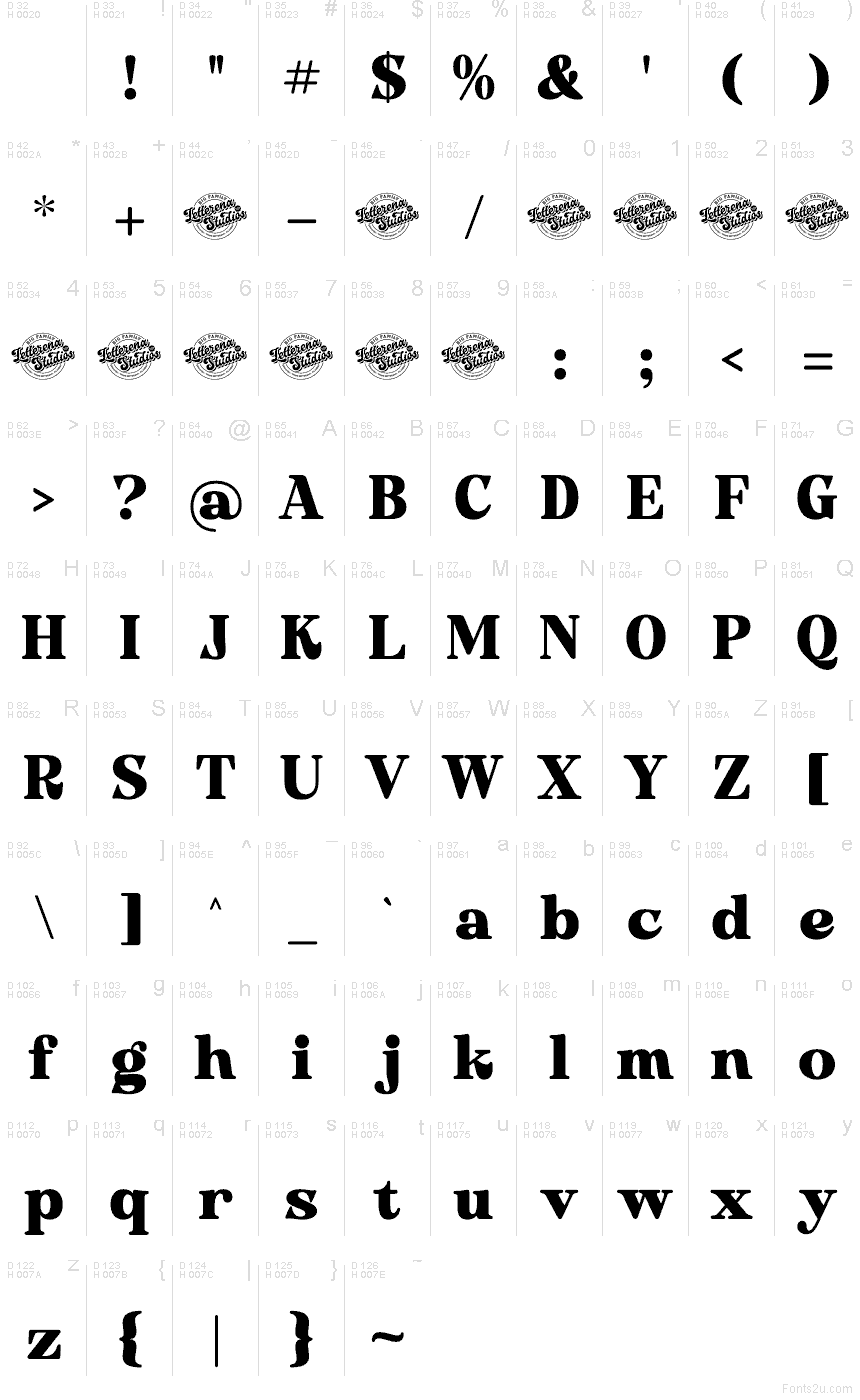
Begsta Pearl DEMO VERSION
Begsta Pearl aus dem Hause Letterena Studios ist eine kostenlose Retro-Serifenschrift mit dem unbeschwerten Lebensgefühl der 1970er Jahre. Die Buchstaben wirken üppig und fast ein wenig fließend, mit schweren Rundungen, engen Verbindungen und tropfenartigen Details, die der Schrift einen verspielten, plakativen Rhythmus verleihen – weit weg von formellem Buchsatz.
Sie eignet sich hervorragend für Branding-Projekte, Café-Speisekarten, Albumcover, Verpackungsdesigns und Magazin-Titel, bei denen eine sanfte Vintage-Note gefragt ist. Als kostenlose Schriftart glänzt sie besonders bei kurzen Überschriften, Titelkarten und logoartigen Schriftzügen, da die abgerundeten, vollen Formen selbst kurzen Wortfolgen eine entspannte, unverkennbar nostalgische Ausstrahlung verleihen.